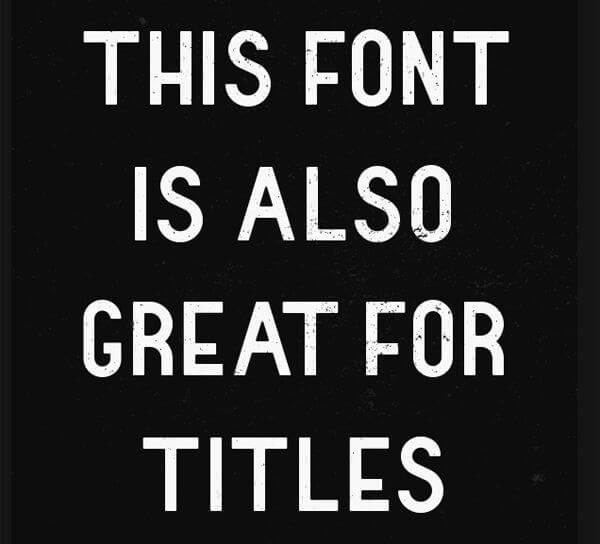
一目を引くデザインを実現!クリエイティブで風変わりなフォント集30選
どんなプロジェクトでも、フォントはデザインの上でとても重要な役割を果たします。選ぶ書体によって、伝えたいメッセージやフィーリングは大幅に変わってしまうのです。しかし、Times New Roman、 Verdanaや Arialなどよく使われる書体以外を使って冒険してみたり、serif やsans-serif フォント以外を使うデザイナーは多くありません。
もし、他と違ったデザインを探しているなら、無料で使えるクリエイティブで一風変わったフォントはいかがでしょうか。最近リリースされた(ここ6カ月間)クリエイティブで無料のフォントを30選集めました!
Rhyder by Adrian Candela
AI Kelso by jagdeep Singh
Newsense by Adrian Candela
Free Vector Font by Rich McNabb
Ontwerp by Emraan Mayow
Wamed by Laura Pol
Glitch by James Stone
Valkyrie by Hendrick Rolandez
London by Antonio Rodrigues Jr
free quirky London font typeface
Gayatri Sans Serif by jagdeep Singh
Istanbul by Kutan Ural
Newgeo by Lettering Shop
Portica Regular Typeface by Michael Nunes
Inky by Fie Clarke
Lunch Invitation by Rich McNabb
Verano (Tipo) by Joan Alegret
Quirky Nots by Amit Jakhu
Hanoi Typeface by Alex Dale
Salt & Foam by Anna K.
Higher by Marisa Passos
Matchup Typeface by Ryan Welch
Brandon Text Medium by HVD Fonts
Ridge Typeface by Erika Mackley
Moonshiner by Mattox Shuler
Haymaker by Trevor Baum
Good Intent Typeface by Pedro Veneziano
Facunda by Bu!
Vincent by Ben Suarez
Magna Typeface by Hendrick Rolandez
Citizen Slab Regular by Joel Felix